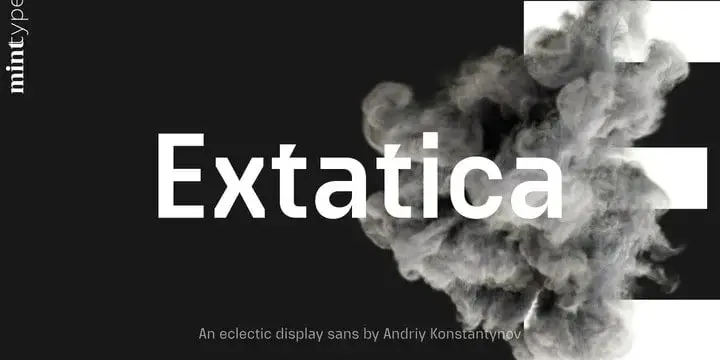
A fonte ‘Extatica Sans Serif Font’ é uma família de fóntes sem serif que traz ao seu design uma sensação moderna e geométrica. Inspirada na estética grotesca, a ‘Extatica Sans Serif Font’ apresenta um toque humanista, tornando-a perfeitamente adaptável para qualquer projeto gráfico onde se exige um estilo contemporâneo. Esta fonte é tão versátil quanto funcional: ela oferece 8 pesos diferentes e correspondentes itálicos, garantindo uma diversidade de uso. Além disso, sua rica gama inclui alternativas estilizadas e recursos OpenType, o que a torna ainda mais robusta para diferentes tamanhos e ambientes de visualização. Para os criadores de design que buscam um fóntes sem serif moderno e elegante, a ‘Extatica Sans Serif Font’ é uma opção perfeita. Suportando todos os idiomas europeus baseados na lenda latina, bem como os principais sistemas de escrita da Rússia (Cyrillic), ela abrange uma vasta gama linguística. Esta fonte não apenas oferece um design contemporâneo e sofisticado para o seu projeto, mas também uma versatilidade rica em recursos que irá impressionar qualquer usuário. Obrigado a todos os designers por se unirem à nossa missão de fornecer as melhores fontes do mercado, a ‘Extatica Sans Serif Font’ é certamente um dos destaques da nossa gama de produtos.